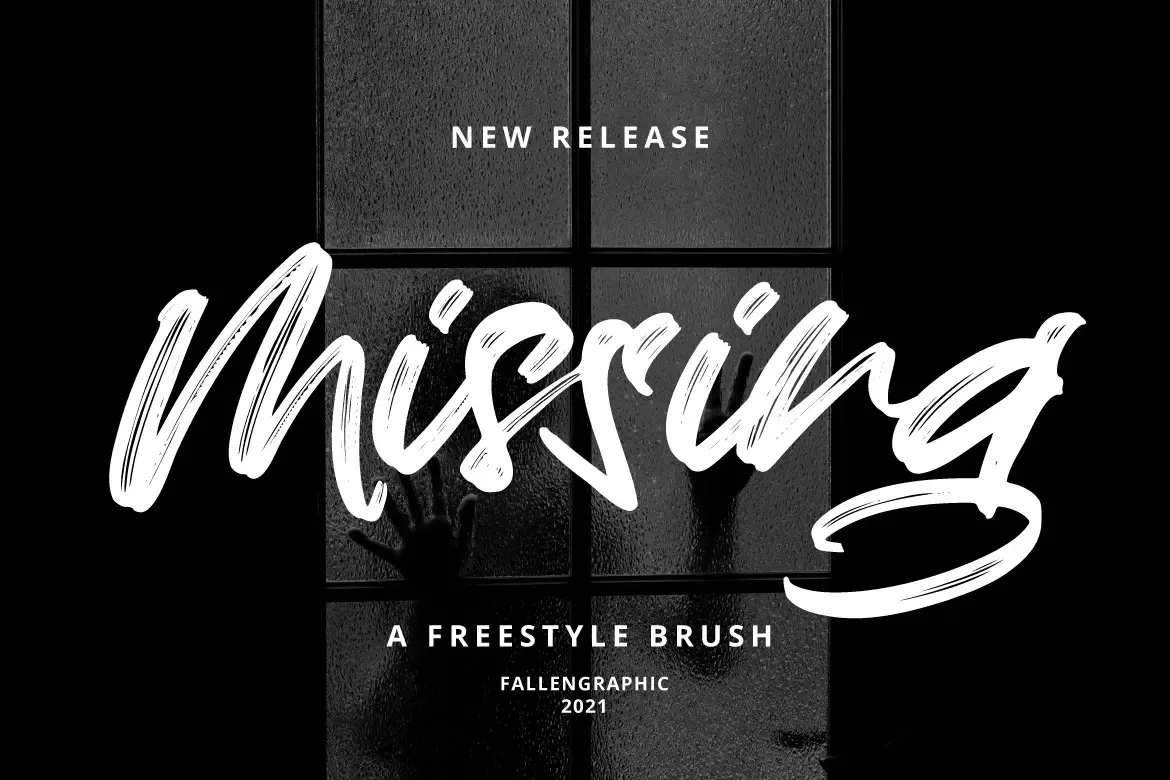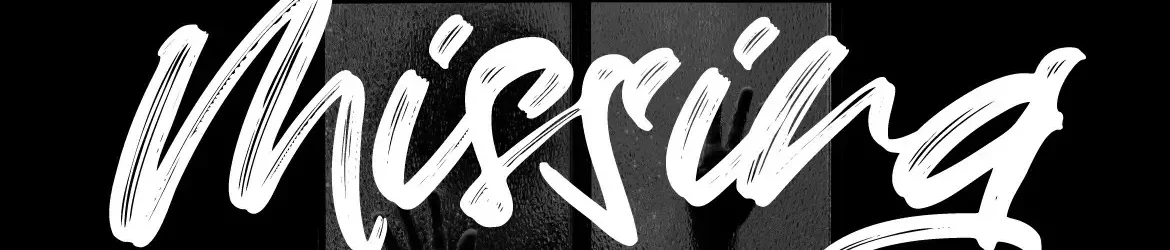
Missing Font – Download Grátis
Esta é uma nova adição à família das fuentes script do Missing Font, uma opção perfeita para designers que buscam elementos contemporâneos e leves. Com uma textura natural de traçado a mão, ela se destaca por seu estilo fluido e dinâmico. Ideal tanto para aplicações de marca como para as frases mais inspiradoras ou reflexivas, esta fonte adiciona um toque especial e sofisticado aos seus projetos. Ela é perfeita para dar uma sensação a mais de personalização aos seus designs, seja ele em branding, citações ou qualquer outro tipo de projeto. Sem dúvida alguma, este é um recurso gráfico que pode potencialmente revolucionar o seu trabalho de design.